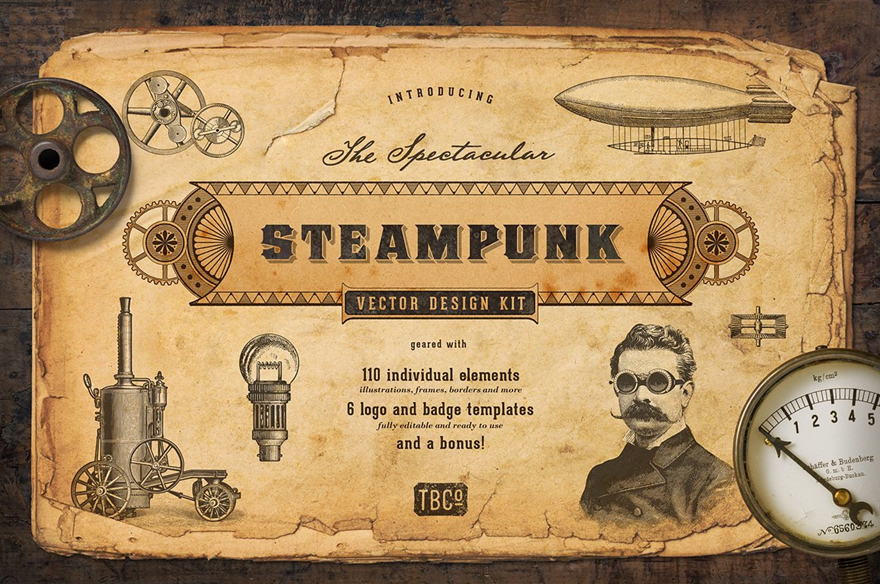
7+ meilleures polices Steampunk et victoriennes
Publié: 2019-04-17L'ère victorienne est grandement romancée. La littérature et les médias prennent souvent des notes de l'esthétique, de la culture industrielle, du design et de l'art de l'époque. La typographie n'est pas différente. L'ère de la vapeur est connue pour ses scripts et ses gravures magnifiquement stylisés, et la popularité du steampunk, un sous-genre de science-fiction dans lequel la puissance de la vapeur est la force motrice de la technologie plutôt que du pétrole, a conduit à un certain nombre de belles polices et des polices de caractères que vous pouvez utiliser pour donner à vos créations un aspect à la fois industriel et raffiné. Nous allons vous montrer quelques-uns de nos favoris.
1. Steampunk
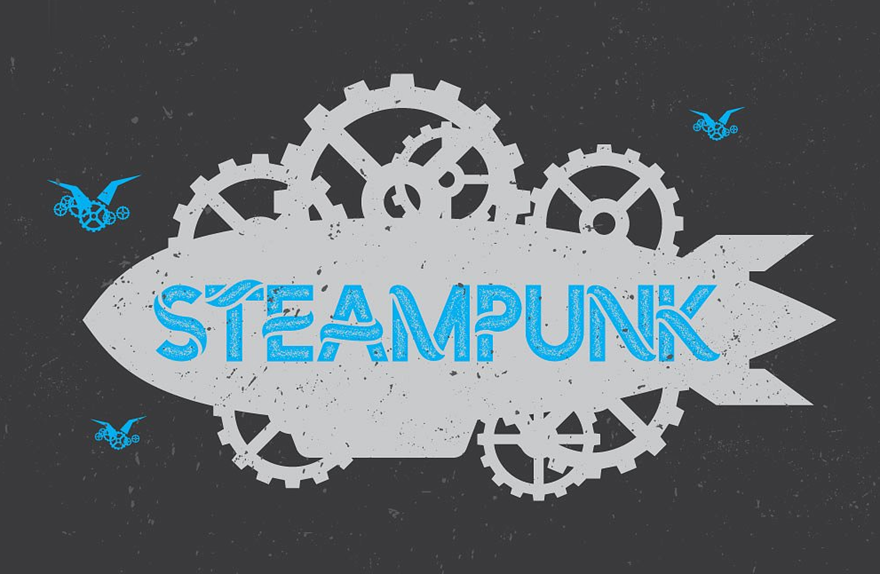
Lorsque vous dressez une liste des meilleures polices steampunk, ce n'est probablement pas une mauvaise idée de commencer par une simplement intitulée steampunk . Après tout, une police steampunk nommée steampunk doit capturer ce que les concepteurs recherchent. Combinant le look industriel que les fans de steampunk adorent avec l'élégance fluide et douce de l'ère victorienne, cette police de pochoir vaut bien le prix de 10 $.
2. Casquettes Steamcog
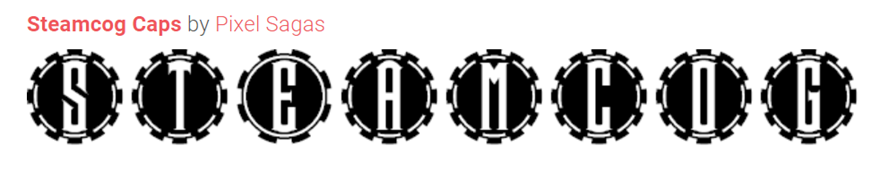
Steamcog Caps est une police vraiment intéressante. Ce n'est pas le genre de police avec laquelle vous tapez vraiment beaucoup. Presque une police d'icônes, Steamcog Caps est fantastique pour les accents et la décoration et pour les utiliser comme lettrines dans vos créations. Parce qu'il s'agit d'une police tout en majuscules, il n'y a peut-être pas une tonne de variation, mais la forme unique d'engrenage/d'engrenage et l'inclusion de symboles de ponctuation de base font que celle-ci vaut la peine d'être téléchargée car le prix est tout à fait correct. Libérer.
3. Héméra II
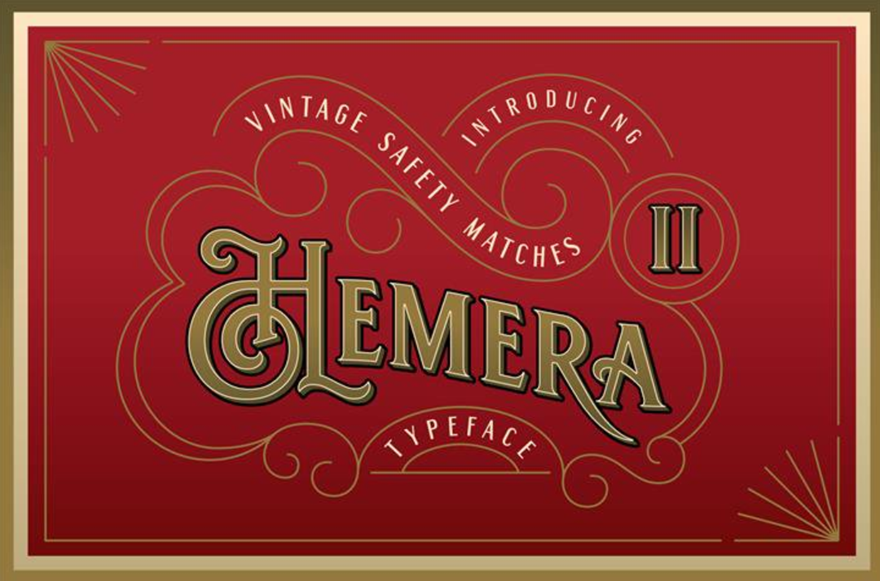
Chez Elegant Themes, nous n'approuvons pas la vente d'huile de serpent. Mais si vous décidez d'emprunter cette voie et que vous avez besoin de faire de la publicité pour votre propre tonique à l'huile de serpent, Hemera II est la police vintage/victorienne parfaite pour attirer l'attention des gens. Venant avec uniquement les lettres de l'alphabet anglais, Hemera est mieux utilisé pour des choses telles que les logotypes et la publicité, plutôt que pour la copie longue. C'est gratuit, cependant, contrairement à toute cette huile de serpent qu'il pourrait aider à vendre.
4. Police Steampunk
Une autre police de caractères éponyme, S teampunk Font est spécialement conçue pour le logotypage. Le niveau de détail que le concepteur a mis dans cette police est incroyable, avec plusieurs couches, couleurs et nuances disponibles, en plus des personnages fabriqués à partir de pièces plus petites et assemblés comme les machines qu'ils imitent. Si vous optez pour cette ambiance steampunk hardcore ou industrielle avec votre conception, vous pourriez faire bien pire que de jeter 14 $ pour cela.
5. Starship (et 7 autres familles de polices !)
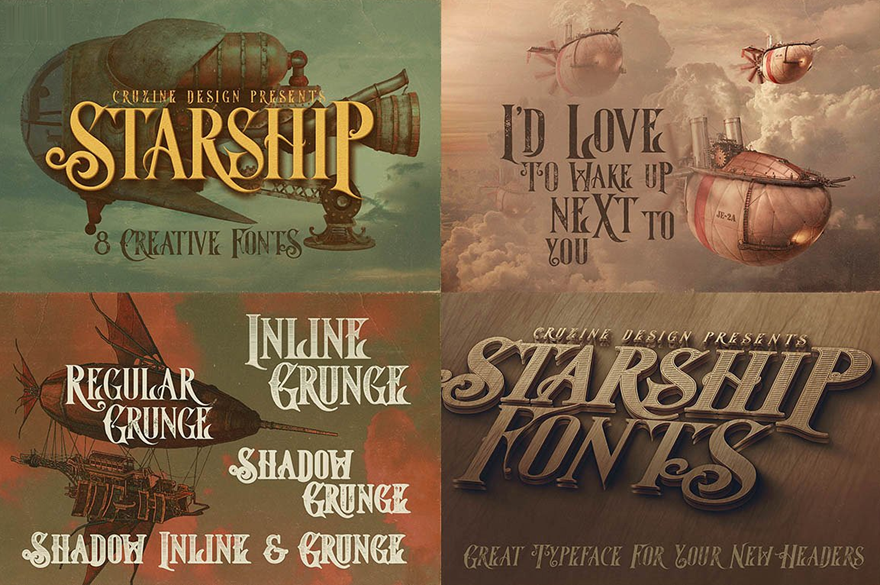
Ce pack est une bonne affaire. Pour 8 $, non seulement vous obtenez Starship (l'une des meilleures polices steampunk, capturant la fantaisie de l'époque, l'élégance de la culture et la puissance de la technologie), mais vous obtenez également Hallowen, Zalora, Geno , Kiki, Skywalker, Meravin et Venomous (qui peuvent tous être vus et en démonstration ici). Dans chacune de ces 8 familles de polices, vous obtenez un total de 49 polices que vous pouvez manipuler pour améliorer et peaufiner à peu près n'importe quel projet de la manière que vous souhaitez. Bien sûr, les polices gratuites sont géniales. Mais 49 polices pour 8 $ sont assez proches de la gratuité. Et ils sont tous de haute qualité et faciles à recommander.
6. Steampunk fabuleux
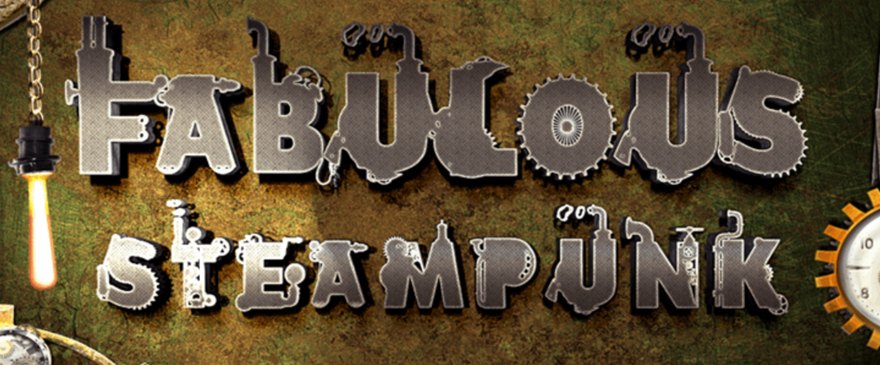
Rarement les gens titrent leurs polices de manière aussi juste que celle-ci. C'est vraiment une fabuleuse police steampunk. S'inspirant du côté industriel et technique de l'ère victorienne, Fabulous Steampunk est à la fois facile à lire et utile. Comme certaines des autres polices ici, vous ne voulez probablement pas faire un travail long et petit avec. Mais vous ferez de grandes choses pour les logos et tous les projets qui nécessitent des tailles de police plus grandes et qui ont des espaces à revendre. Cette police steampunk particulière se distingue par l'attention portée aux détails sur les personnages individuels, tels que les rouages, les engrenages, les tuyaux et la vapeur elle-même fonctionnant comme des empattements pour certains personnages, mais pas tous. L'exclusion de certains caractères ayant des empattements rend ceux qui se démarquent encore plus.
De plus, la police comprend plusieurs symboles, vous n'aurez donc pas à rechercher une police de caractères secondaire pour terminer votre conception. Fabulous Steampunk peut être téléchargé gratuitement. Le concepteur demande un don de 6 $ pour des utilisations commerciales. Cela nous semble assez raisonnable.
7. Teslafont
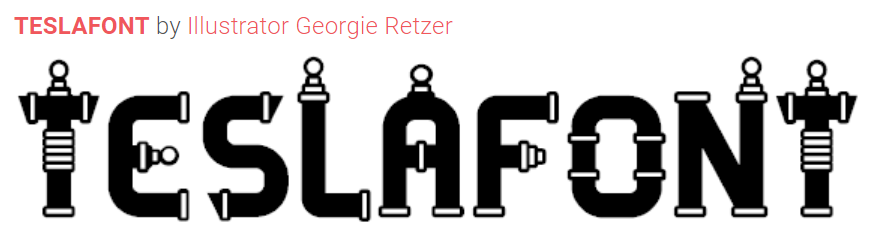
Une liste mentionnant l'ère victorienne ou steampunk sans référence à Nikola Tesla serait négligente et se déroberait à ses responsabilités. Nous voici donc avec l'incroyablement belle Teslafont. Conçue d'après les propres « émetteurs grossissants » de l'inventeur, cette police capture le rétrofuturisme que nous aimons dans le steampunk et l'esthétique victorienne. Bien qu'il ne soit pas tout à fait futuriste, ce texte peut être utilisé pour indiquer une vision prospective et un progrès, tout comme son homonyme l'a fait lui-même. Teslafont est livré avec 98 caractères complets. Cependant, seules les lettres de l'alphabet sont agrémentées des bobines Tesla elles-mêmes. En tant que police gratuite, vous voulez absolument l'ajouter à votre bibliothèque.